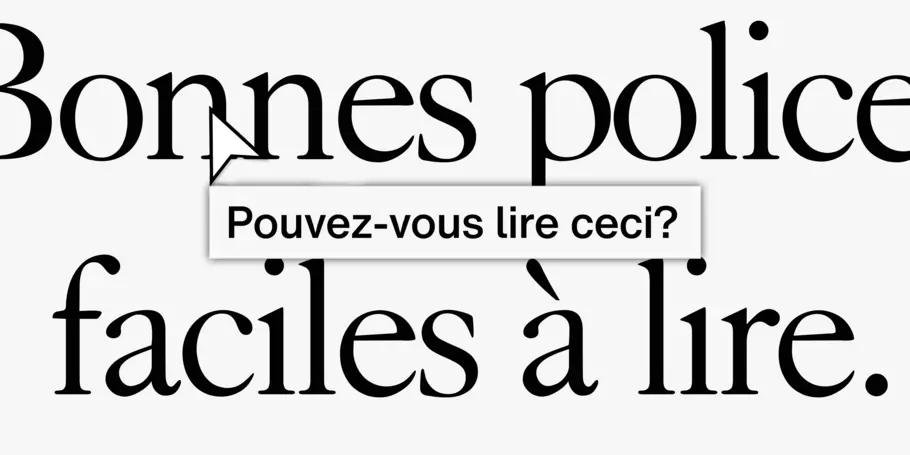
Le texte de votre site Web répond-il aux normes d’accessibilité ?
Plus que jamais, le choix des polices de caractères est essentiel pour un design fonctionnel.
​​​En 1990, aux États-Unis, le Americans with Disabilities Act (ADA) interdit la discrimination à l’encontre des personnes handicapées. En France, il faut attendre la loi du 11 février 2005 pour instaurer une politique qui impose « l’égalité des droits et des chances, la participation et la citoyenneté des personnes handicapées ». L’accessibilité devient alors obligatoire et concerne tous les éléments du déroulement de la vie collective, y compris les moyens de communication publique en ligne.
Les entreprises et les organisations de toutes sortes doivent comprendre et respecter la nécessité de ces normes. C’est d’autant plus crucial pour les domaines de la finance, de la santé, de l’éducation et, bien sûr, de l’administration. Si les directives pour l’accessibilité peuvent sembler écrasantes au premier abord, elles ne font en réalité que prescrire, de manière spécifique, une conception design nette et réfléchie, qui met la priorité sur l’expérience de chacun des utilisateurs.
Les normes.
​Les normes pour l’accessibilité – la norme européenne EN 301 549 et la norme internationale WCAG 2.1 – sont toutes deux contenues dans un seul référentiel : le RGAA.  Ce référentiel est fait pour vous permettre de faciliter, structurer et tester la mise en conformité de vos sites et services numériques.
Pour les designers et les développeurs, quatre termes sont à retenir en guise de feuille de route : perceptible, utilisable, compréhensible et robuste. Ce sont les quatre principes généraux qui résument l’accessibilité numérique des contenus Web. Ces objectifs peuvent paraître simplistes. Mais pour les personnes ayant des difficultés visuelles, auditives ou physiques, ces éléments essentiels sont souvent involontairement compromis par des choix de design quotidiens.
Chacun de ces 4 principes est étayé par 13 règles (ou objectifs) spécifiques en matière de design et d’expérience utilisateur. Ces règles sont elles-mêmes déclinées en critères de succès de conformité, répartis en trois niveaux : A (le plus bas), AA (intermédiaire) et AAA (le plus élevé). Plus ces critères sont respectés, plus le taux d’accessibilité d’un contenu ou site Web est considéré comme conforme. Le niveau A représente les critères minimaux requis pour prétendre avoir un contenu Web accessible. Les critères AAA permettent d’obtenir un niveau de conception dont l’accessibilité est jugée totalement conforme. (Le niveau AA se situe évidemment à mi-chemin entre les deux).
En France, ces normes sont soumises à des obligations légales. En plus de la conformité totale au ​​RGAA, chaque site ou service en ligne doit mettre à disposition une déclaration d’accessibilité, mentionner en page d’accueil le niveau de conformité (totalement conforme, partiellement conforme ou non conforme) et proposer un lien vers un schéma pluriannuel de mise en accessibilité numérique. L’oubli de ces obligations déclaratives peut entraîner des sanctions allant jusqu’à 20 000 euros.
Tout cela peut sembler difficile à assimiler. Mais de nombreuses ​​ressources vous permettent de comprendre plus en détail les directives et leurs critères respectifs de conformité. Dans le cadre de cet article, nous nous concentrerons sur trois composantes générales relatives au texte.
Comment utiliser la couleur pour rendre votre site Web accessible aux personnes handicapées ?
Depuis longtemps, les designers utilisent la couleur pour établir une hiérarchie et une différenciation sur une page. Cependant, il est important de considérer l’impact que cela peut avoir sur la lisibilité pour les personnes ayant des difficultés visuelles, notamment le daltonisme. Selon la ​​norme internationale WCAG 2.1, la couleur ne doit pas être « utilisée comme la seule façon de véhiculer de l’information, d’indiquer une action, de solliciter une réponse ou de distinguer un élément visuel. »
En d’autres termes, la couleur doit être accompagnée d’autres éléments de design pour indiquer des phrases importantes dans un texte, distinguer des instructions ou encore des appels à l’action.
Les designers doivent donc utiliser la typographie afin de structurer le contenu de manière judicieuse. Par exemple, ils peuvent utiliser une certaine gamme de graisses, de tailles et de styles pour indiquer les titres, les instructions et les call-to-actions. Le site Web de la Harvard Medical School est un bon exemple de la mise en pratique de ce principe. Une seule famille de polices polyvalente peut fournir toute la variété dont vous avez besoin. Mais les designers peuvent aborder ces cas d’utilisation en optant pour des polices différentes selon les objectifs.
Bien sûr, cela ne signifie pas qu’il faut abandonner l’utilisation de la couleur. Les directives mettent simplement l’accent sur le fait que la couleur ne peut pas être la seule caractéristique distinctive d’un texte.
« À l’époque, nous utilisions uniquement la couleur pour montrer la hiérarchie », explique Marc Rust, directeur principal de la création chez Boston Digital. « Aujourd’hui, pour préserver la lisibilité et garantir l’accessibilité, nous utilisons la taille de la police plutôt que la couleur. Plus que jamais, le choix des polices de caractères est essentiel pour un design fonctionnel.
Cela dit, si l’on veut trouver un équilibre entre l’accessibilité et le design d’une marque, disposer des bons outils est essentiel. Parmi ces outils, pensez à une typothèque de caractères fiable, qui offre une gamme de polices très lisibles dans un large éventail de styles. S’il n’existe pas de programme de certification – ou quoi que ce soit de ce genre –  pour approuver certaines polices officiellement, ces recommandations pour l’accessibilité peuvent vous aider à identifier les polices qui correspondent le mieux. Une bibliothèque bien fournie en polices Web vous permettra de développer des designs Web accessibles, que vos clients apprécieront.